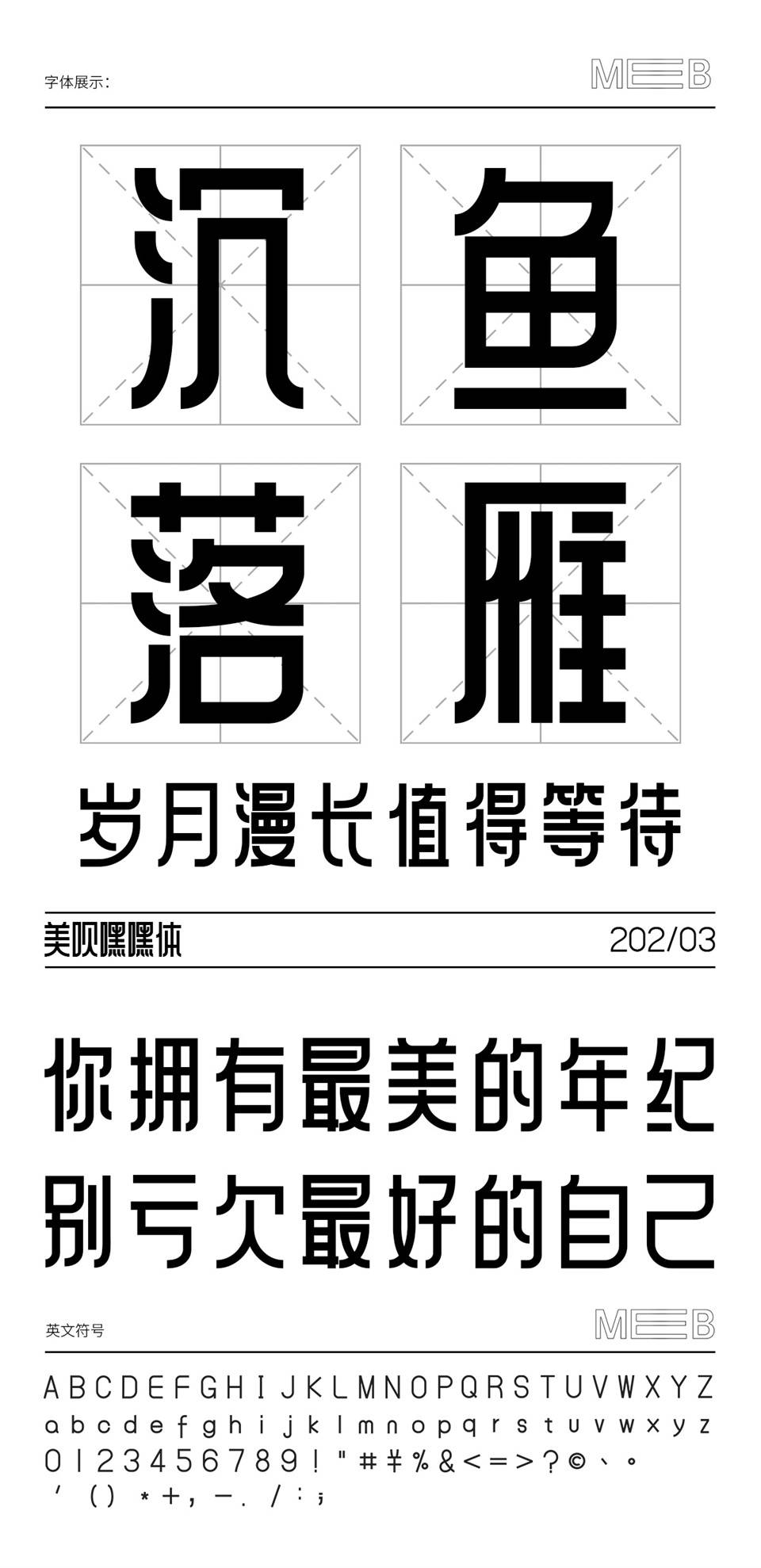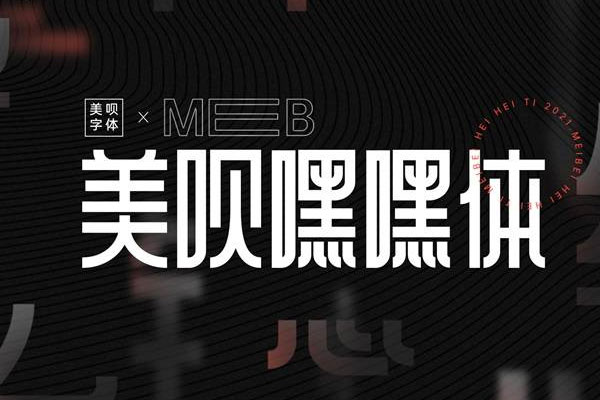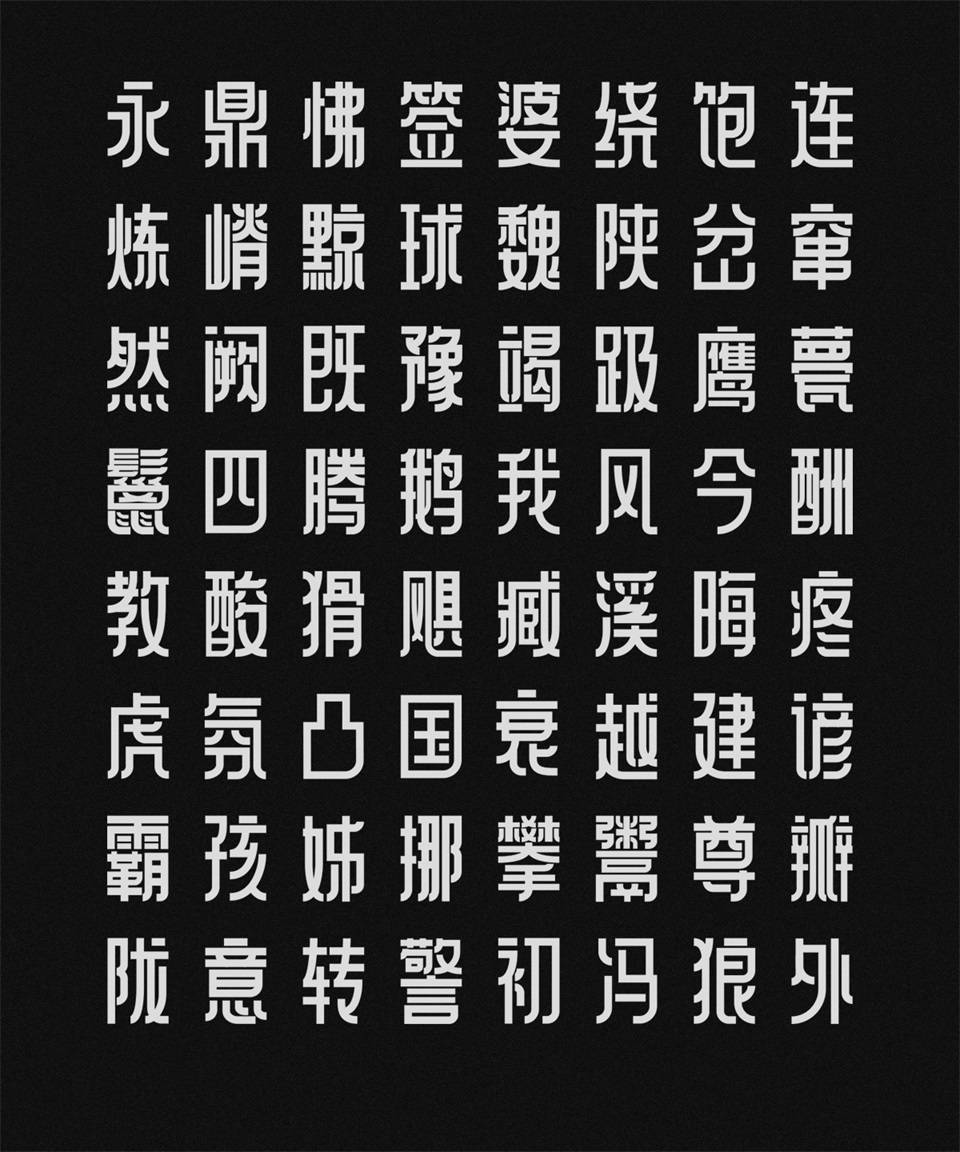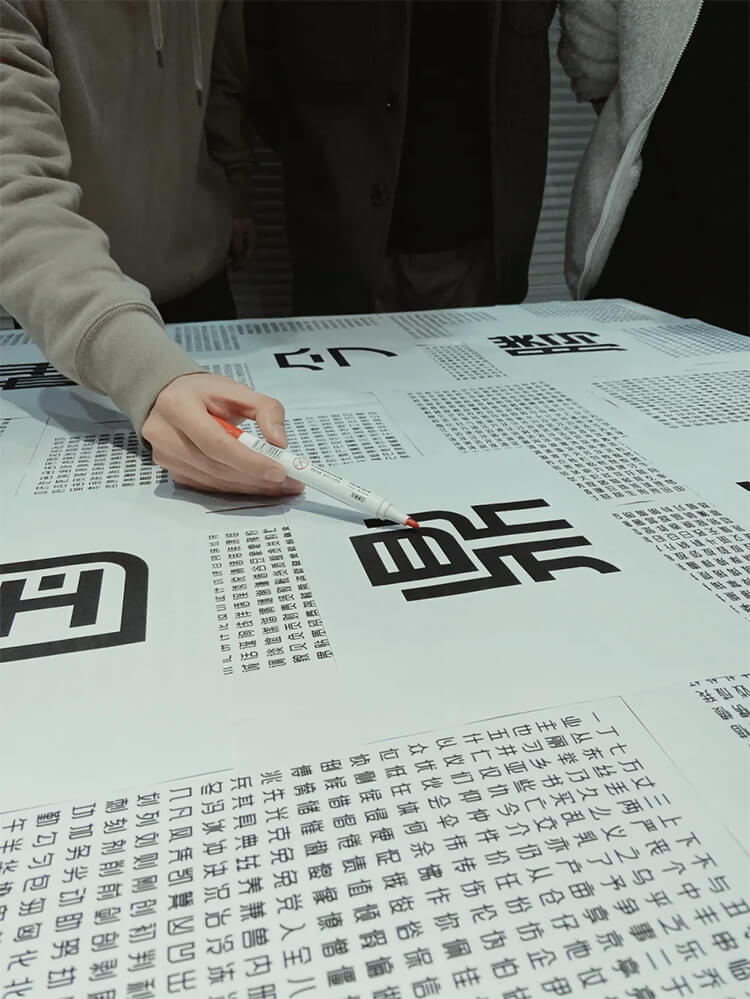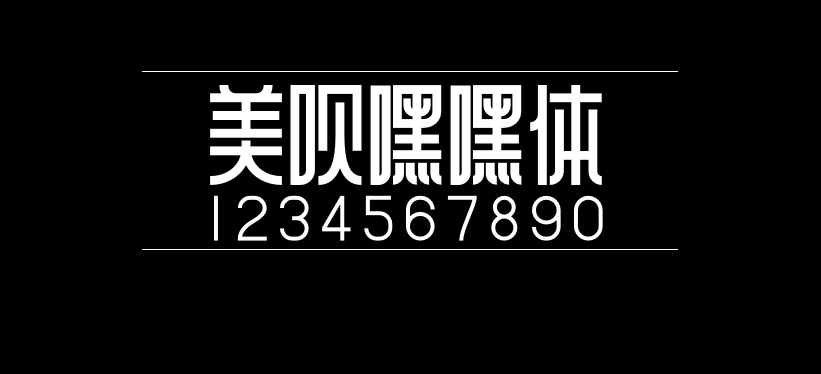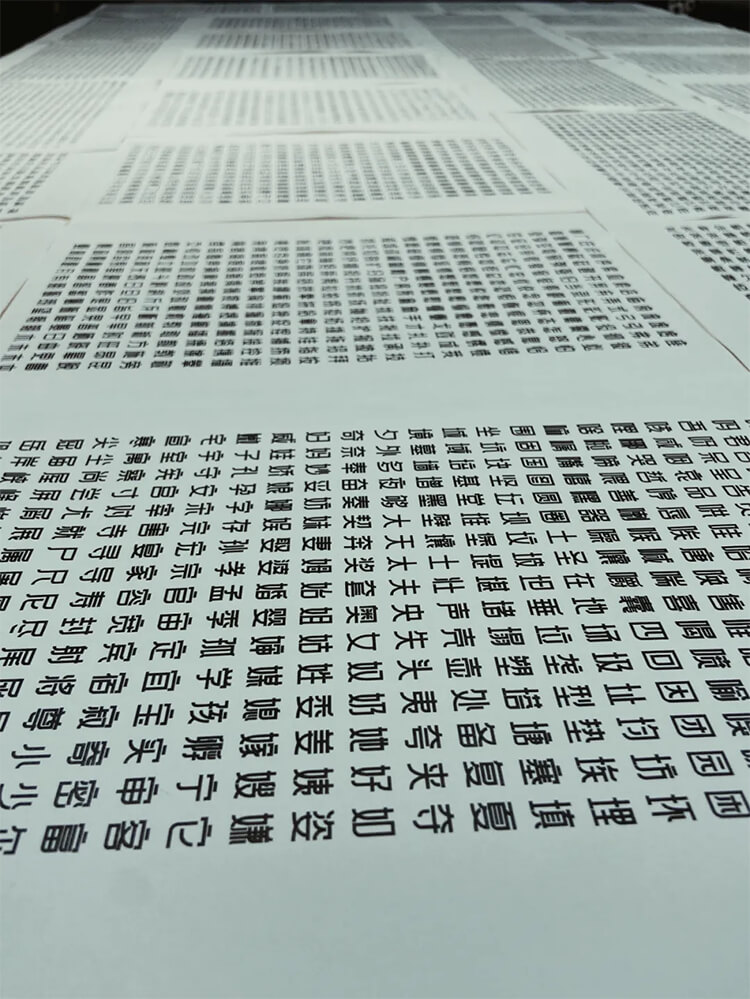
美呗嘿嘿体
美呗嘿嘿体是国内医美平台美呗(www.meb.com)企业内美呗设计团队推出的一款免费商用字体,美呗设计团队为了让品牌符号更加鲜明、让美呗er更有归属感,他们秉承着“开放、合作、创新“公司价值观,就这样开启了一项完全0经验的设计字体的工作!
美呗嘿嘿体字形优雅大方,唯一美中不足就是字符数量不多,目前未达到6763字标准,使用会存在缺字现象,期待美呗团队能尽快更新补齐,也祝愿美呗发展越来越好!
含泪的制作过程
第一步:风格的确立
字库是一项非常耗时耗力的工作,而我们却只能在繁重的日常工作外推进,因此大多时候只能在下班时间完成。为了保障最终字库的效果,我们决定先出三款风格稿。
第二步:50个样字制作
第一批字出来,虽说还是很有成就感,但也不得不承认,团队几乎是做出了七个风格图片。我们花了整整一天时间,逐一复盘了第一批字体,把问题挑出来,讨论出我们理想中字体的样式,在团队不断的讨论及反复修改后,我们的基本的字形及标准终于确定。
第三步:2500个字制作
样字确定完后,设计狮们开始动身制作第一批2500字,当然讨论后避免不了字体的第二遍修改。说是修改,其实是把2500又重新制作一遍
第四步:不断修改,打磨字库
截止时间越来越近,团队不得不加快脚步。
美呗设计团队始终秉承着愚公移山的精神,每天下班后进行字体修改,每天一上班复盘字体。不靠谱靠谱字体小组,没有看过凌晨三点的洛杉矶,但是看过凌晨一点、两点、三点、四点的电脑。修改完第二遍后,字体整体感越来越强,在不断的打磨下,字体基本规则有了,大家已经形成了共识。开始整理偏旁部首,并进行第三第四遍的修改….
第五步:细节收尾
经过错别字检查,导入字库,调整细节等工作后,初版本字体工作终于结束。
也许还不够完美,依然热泪盈眶。整个项目带给我们的,不只是这个字体本身,而是整个做字的过程,我们更加擅长团队协作,我们一起学习,一起进步,一起向上,强迫自己成长,也允许自己有瑕疵。如果你什么也不擅长,那么在当下,竭尽所能做到最好。我们相信,6500字体能越来越好。下一次再见。